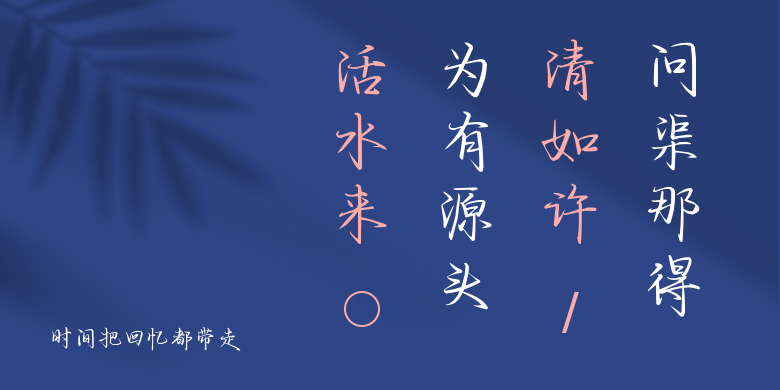
时间把回忆都带走
时间把回忆都带走,这款字体结构工整、笔画清晰,兼顾美观与易读性,适用于标题、正文、海报、包装、LOGO 等多种场景。字形优雅稳定,风格百搭耐看,适配日常排版与创意设计,让文字呈现更舒适、更具质感。时间把回忆都带走一笔一画,皆是细节,以均衡的比例、流畅的线条打造舒适视觉体验,字形端正大气,风格简约现代。无论是商业设计、品牌宣传还是日常排版,都能轻松驾驭,让文字更有格调与力量。时间把回忆都带走字体下载。